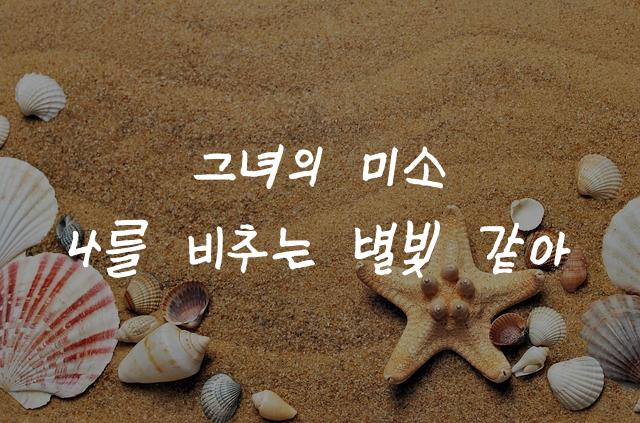
‘그녀-길원옥’ 폰트는 아이들의 색연필로 쓴 듯한 삐뚤빼뚤한 손글씨 스타일을 재현하여 따뜻하고 친근한 느낌을 전달합니다. 각 글자마다 느껴지는 개성과 감성이 풍부한 폰트입니다.
그녀-길원옥은(는)
손글씨, 귀여운 스타일, 레트로, 색연필, 감성적인 계열의 생김새를 가지고 있으며
포스터, 초대장 등에서 자주 활용되며, 효과적인 메시지 전달에 적합합니다.
이 폰트는 크리에이티브, 문화/예술 분야에 잘 어울리며,
감성적인, 예술적인 느낌을 담고 있는 것이 특징입니다.